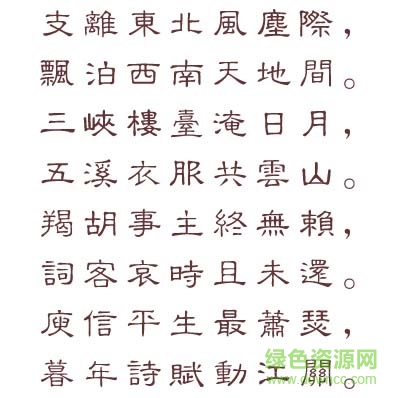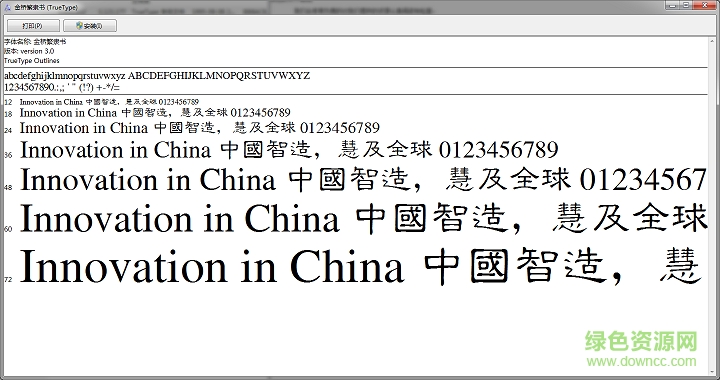
金桥繁隶书
金桥繁隶书金桥字体库中一款繁体隶书字体。字体的间隔距离得体,字体的大小看着也非常的舒服,字形整体略偏宽扁,粗细有变化,给人感觉比较宽广。喜欢的朋友,赶快下载体验吧!
字体说明
字形修长秀美,平正端庄,线条婉转通畅,骨力内涵,挺拔劲健,具有很高的实用性和欣赏
性。该字体实用性强,注重篆法的正确和规范,注重字形美观和风格的统一。
方“铁正筋铁隶精书隶”书以简汉体代隶书结构为基础,字形扁方,参以秦代小篆笔法,特别是以铁线篆书的
线条为主要风格特征,形成既古朴典雅,又富现代气息;既具艺术性,又有实用性的优秀字体。
字型微扁,笔划舒展,构体秀逸平和,古朴庄重,适用于书、报、杂志的标题及正文字,也可作装饰用字。